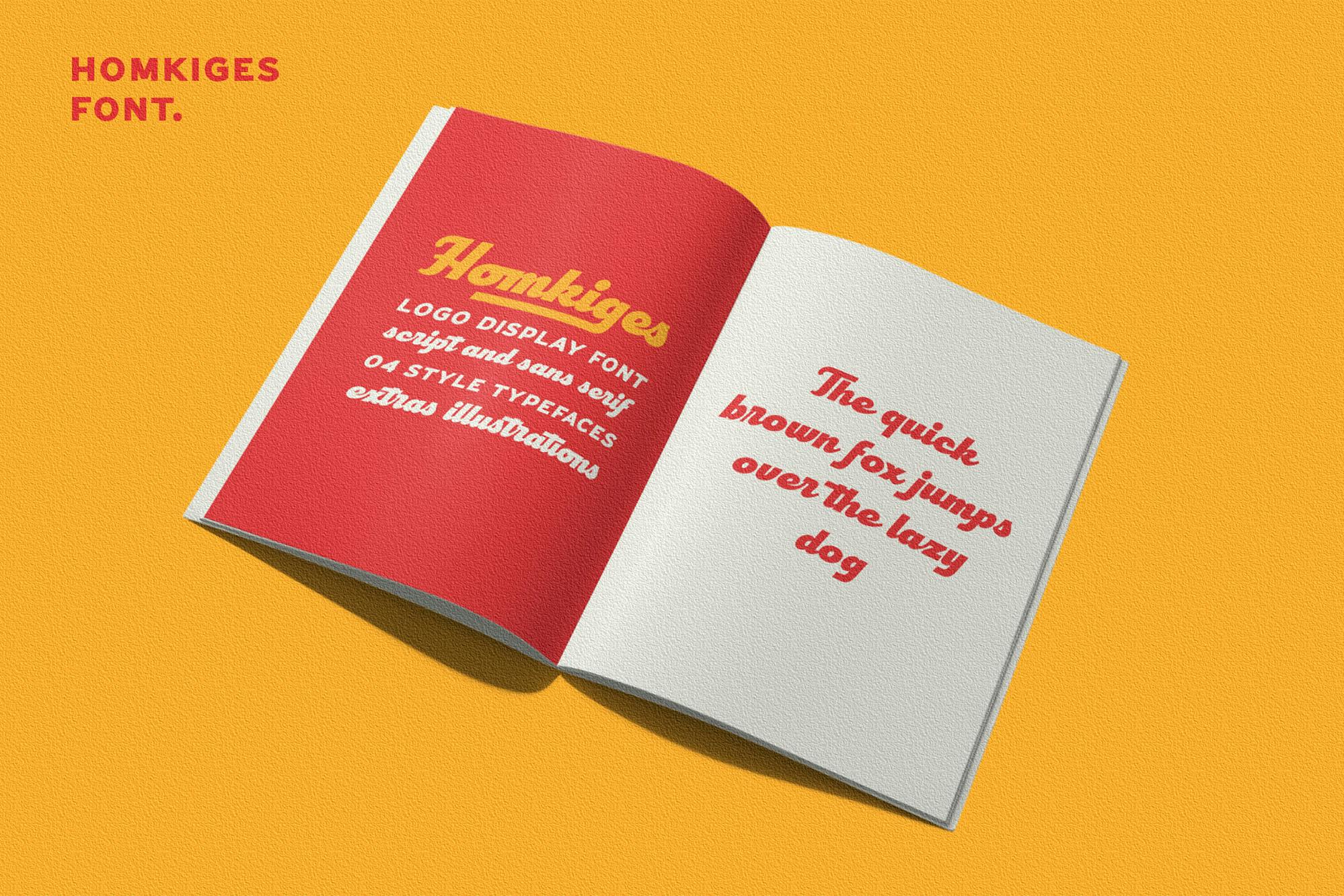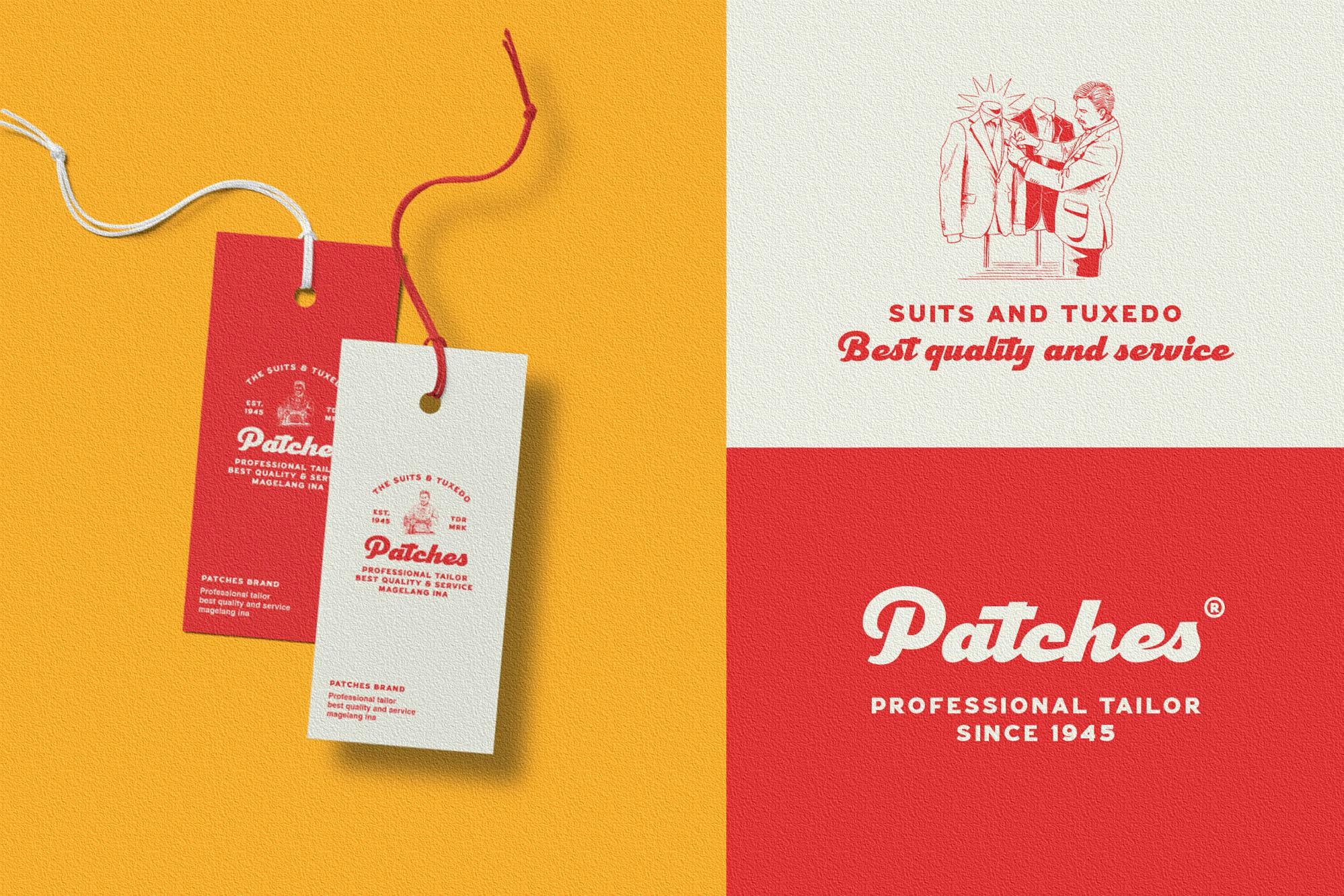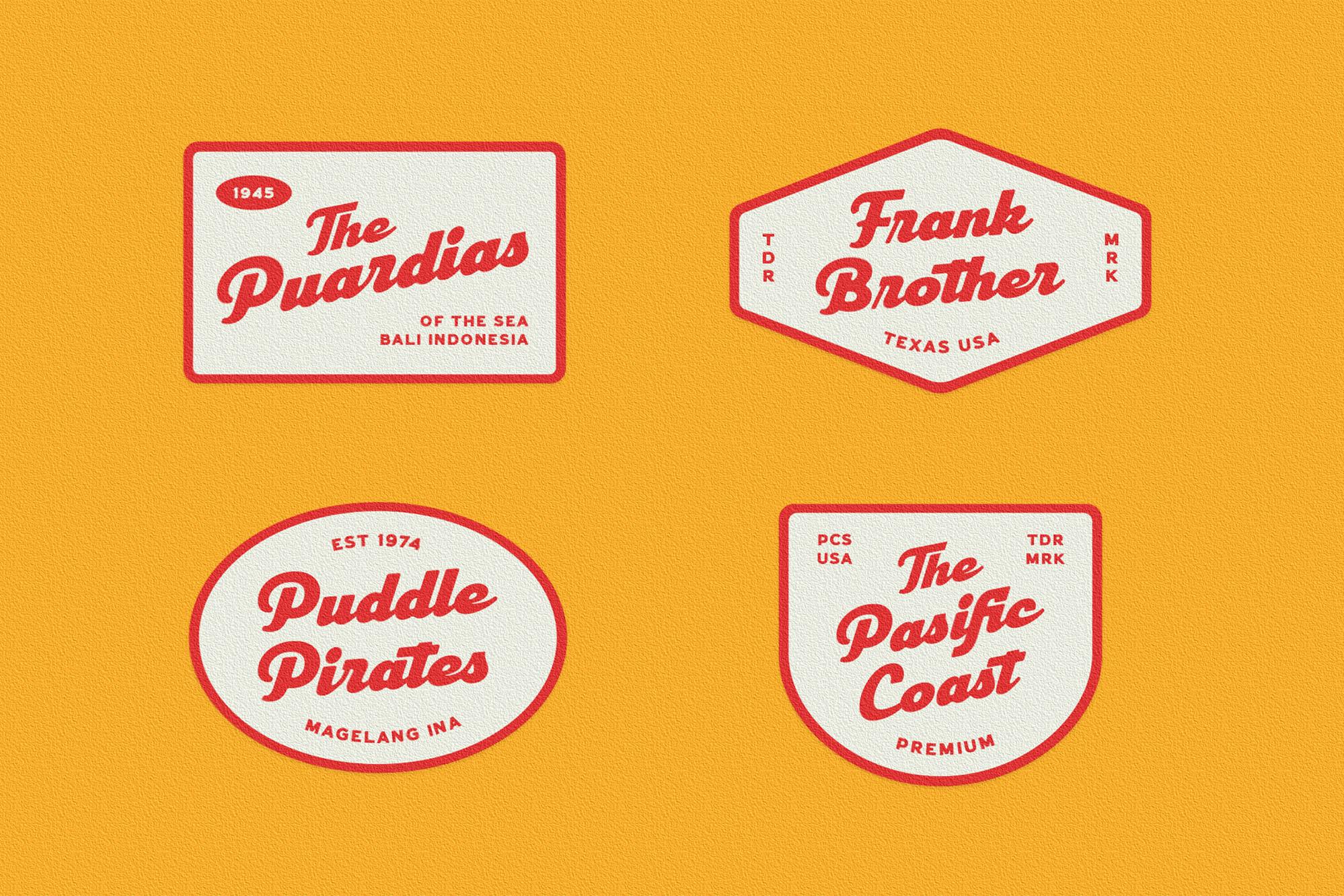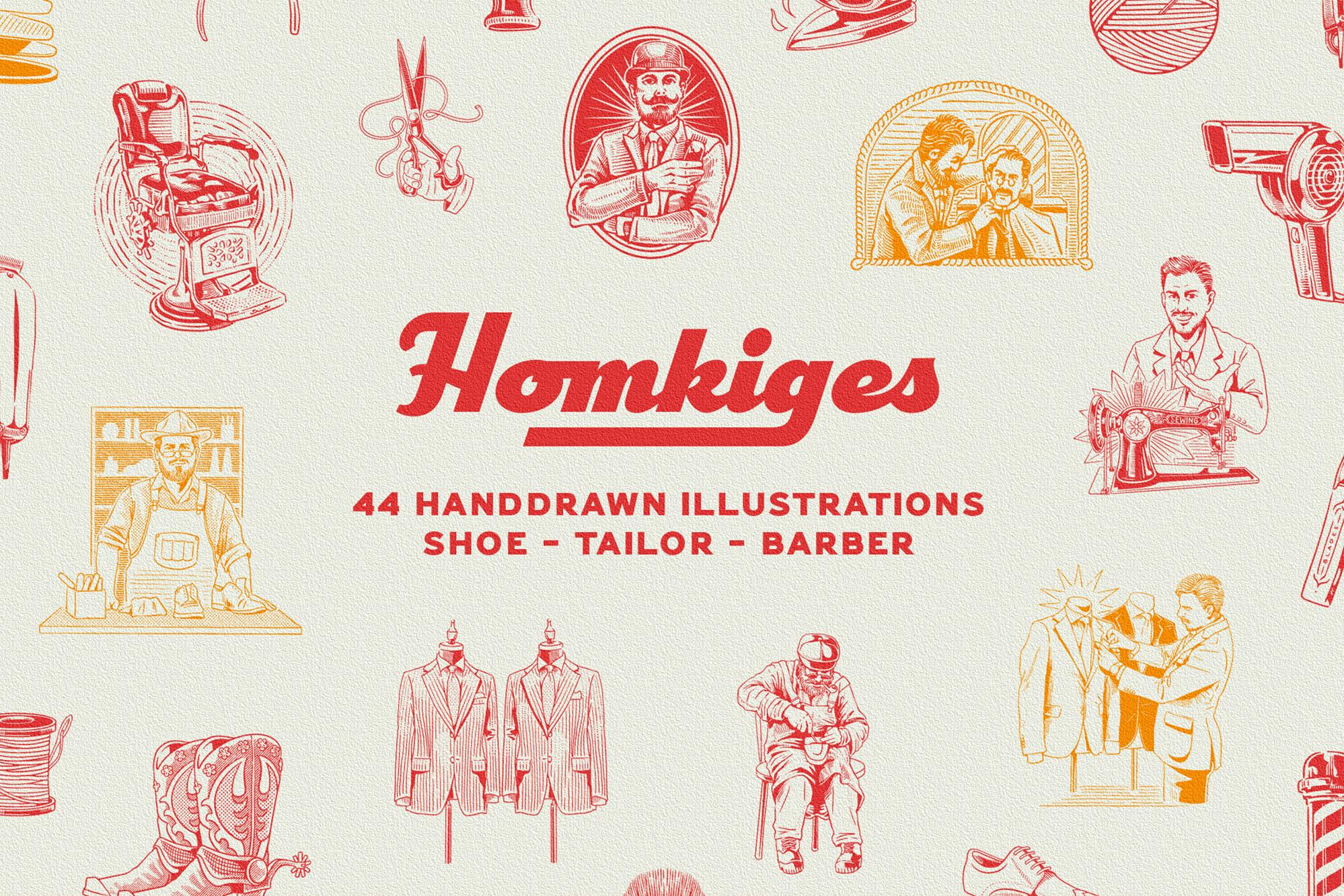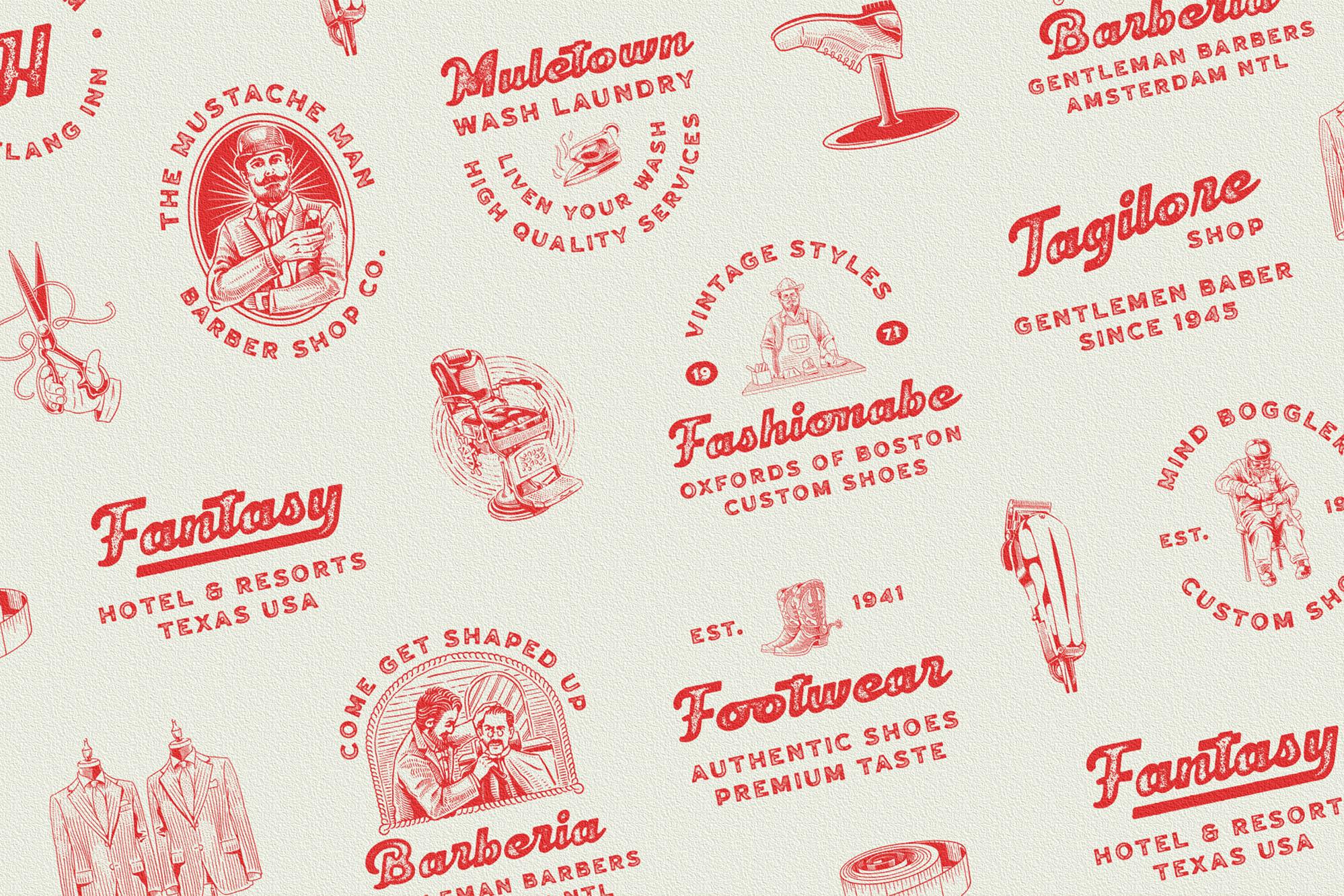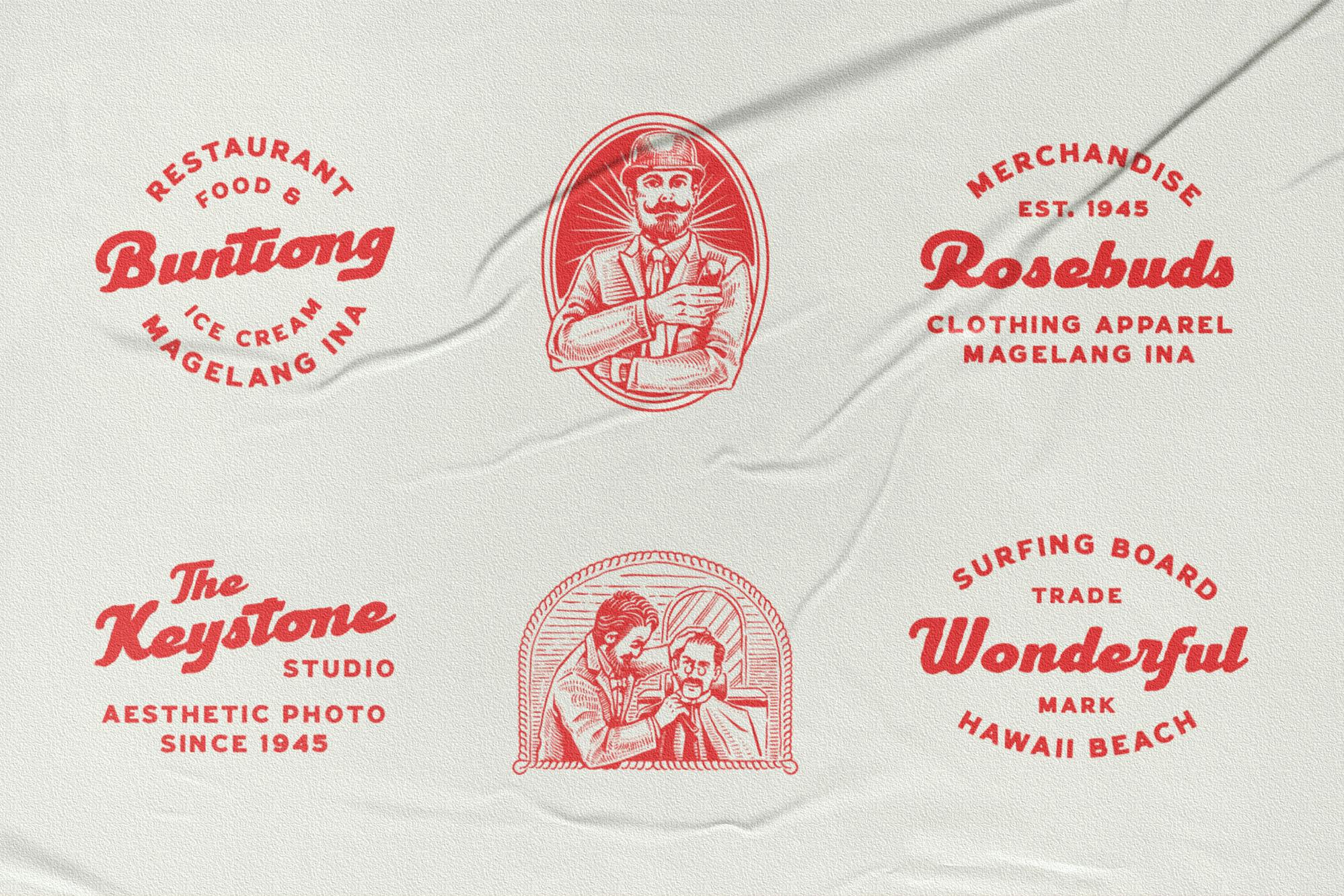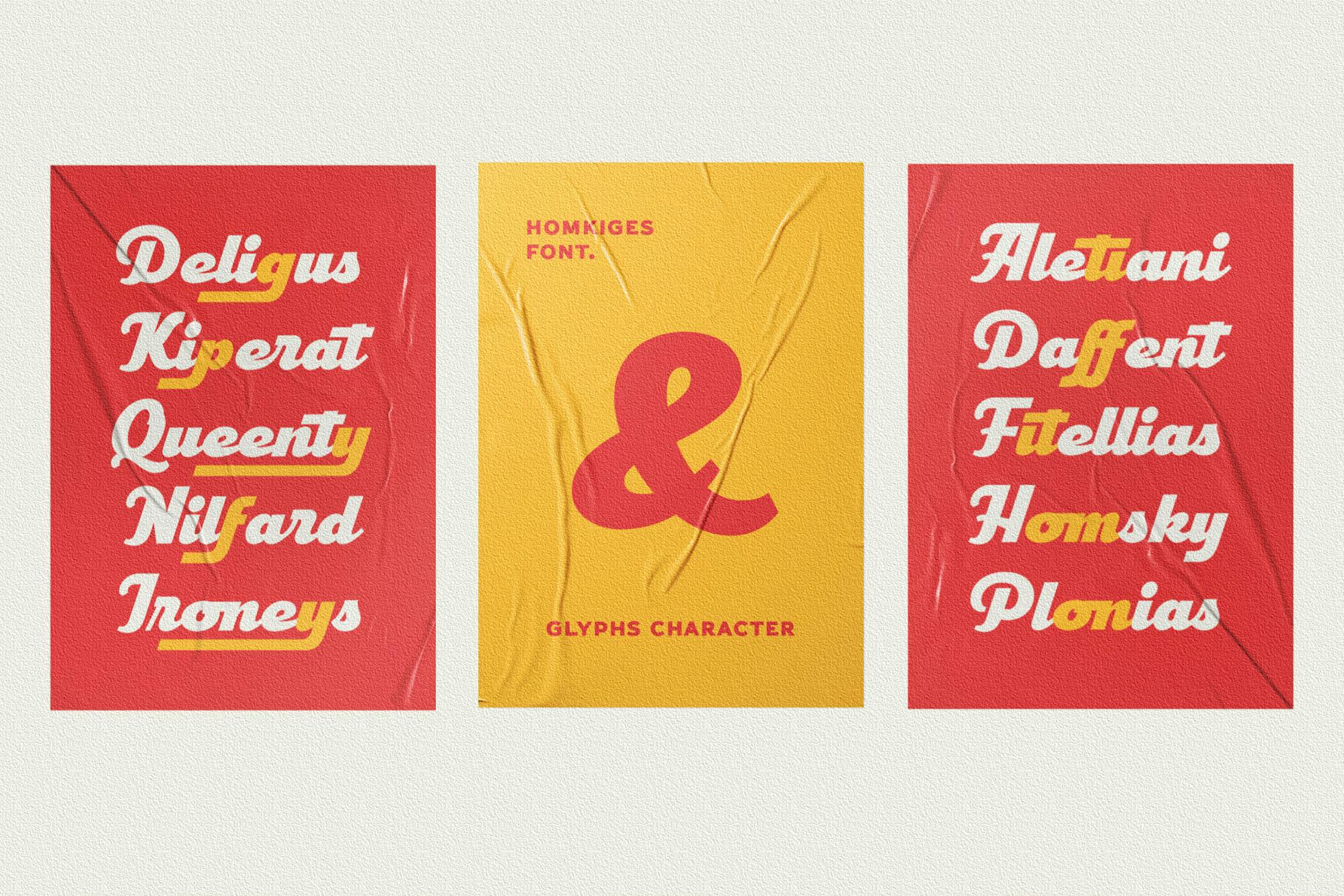
Homkiges Logo Display Font
فونت Homkiges با ۴ استایل مختلف و طراحی منحصر به فرد برای پروژه‌های شما.
مجموعه فونت Homkiges به عنوان یک فونت نمایش برای لوگوتایپ شناخته می‌شود. این مجموعه شامل فونت‌های اسکریپت و سن‌سریف است. هر فونت با ۴ نوع استایل (معمولی، گرد، زبر و مهر) ارائه می‌شود. Homkiges همچنین شامل ۳ بسته تصویر اضافی (کفش، خیاط و آرایشگر) است. این فونت اسکریپت شامل تعدادی جایگزین و ترکیب است. استایل بافتی این فونت شامل تمبرهای مختلف برای حروف بزرگ و کوچک در سن‌سریف می‌باشد. فونت Homkiges در طراحی‌های مختلفی مانند لوگو، پوستر، برچسب، نشان، بسته‌بندی، برندینگ، نقل‌قول‌ها و دیگر طراحی‌های سفارشی قابل استفاده است.
ویژگی‌های Homkiges:
• ۴ نوع استایل (معمولی، گرد، زبر و مهر)
• حروف بزرگ، کوچک، اعداد، نمادها، نشانه‌گذاری، ترکیب و جایگزین در فونت اسکریپت
• تمام حروف بزرگ، اعداد، نمادها و نشانه‌گذاری در فونت سن‌سریف
• فونت مایل در سن‌سریف
• چند زبانه
Homkiges شامل:
• ۱۳ فونت (اسکریپت، سن‌سریف و دینگ‌بات)
• ۴۴ تصویر دست‌کشیده در دینگ‌بات